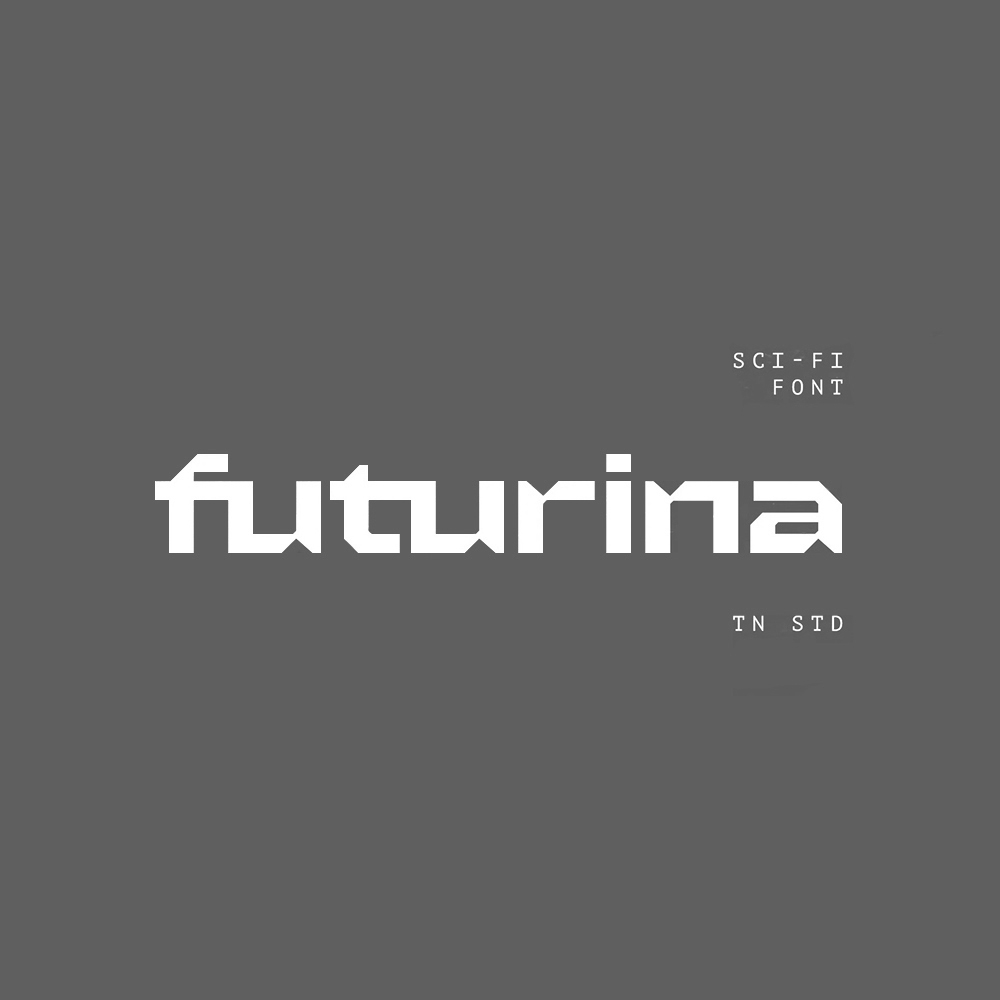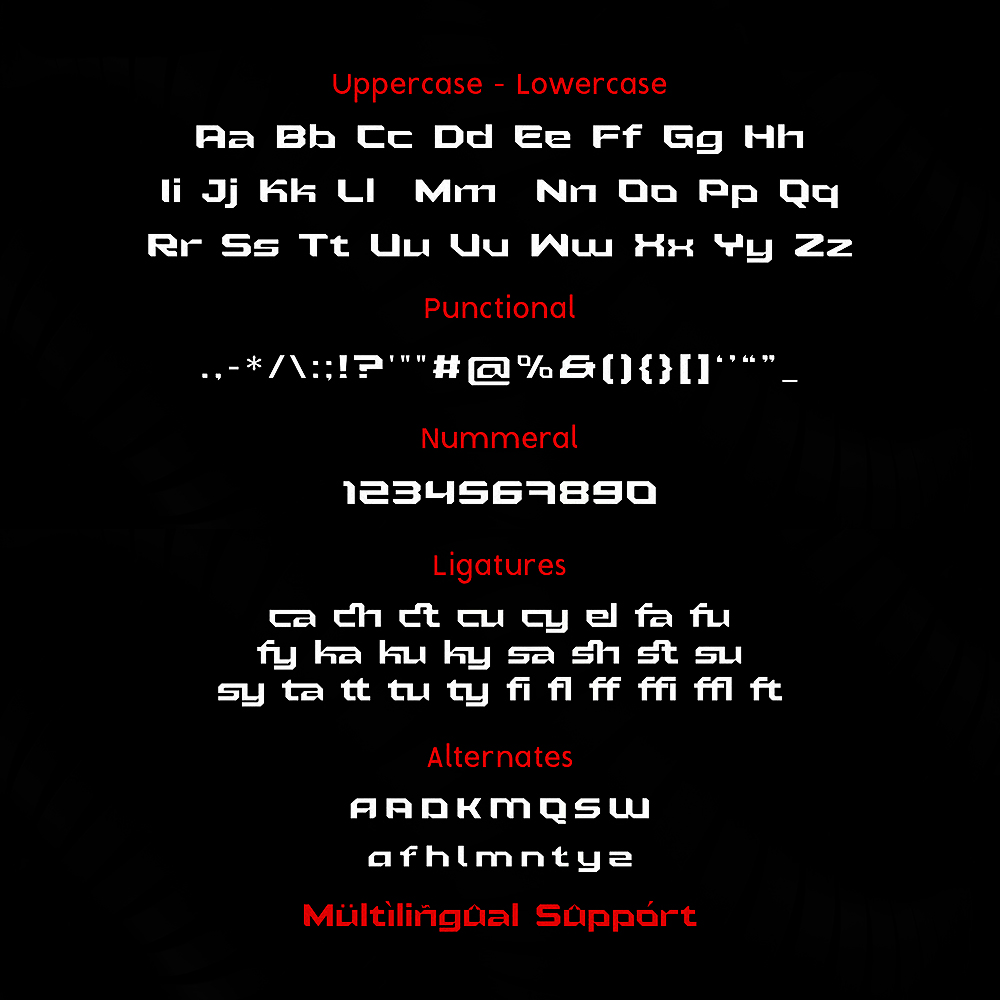
دانلود فونت انگلیسی Futurina Font
فونت پرمیوم و انگلیسی Futurina Font یک فونت سریف است که برای پروژههای آینده شما عالی است. از جمله میتوان به برندسازی لوگو، طراحی سرمقاله، طراحی ورزشهای الکترونیکی، طراحی رترو دهه ۸۰، صنعت بازی/گیم، مسابقات ورزشی، برندسازی سوپراسپرتها، برندسازی ورزشهای الکترونیکی، پوسترهای موسیقی، طراحی وبسایت، طراحی تبلیغات مدرن، نقل قولهای پوستر، عناوین/جلد کتاب، رویدادهای ویژه و موارد دیگر اشاره کرد.
مزایای استفاده از فونت لاتین Futurina چیست؟